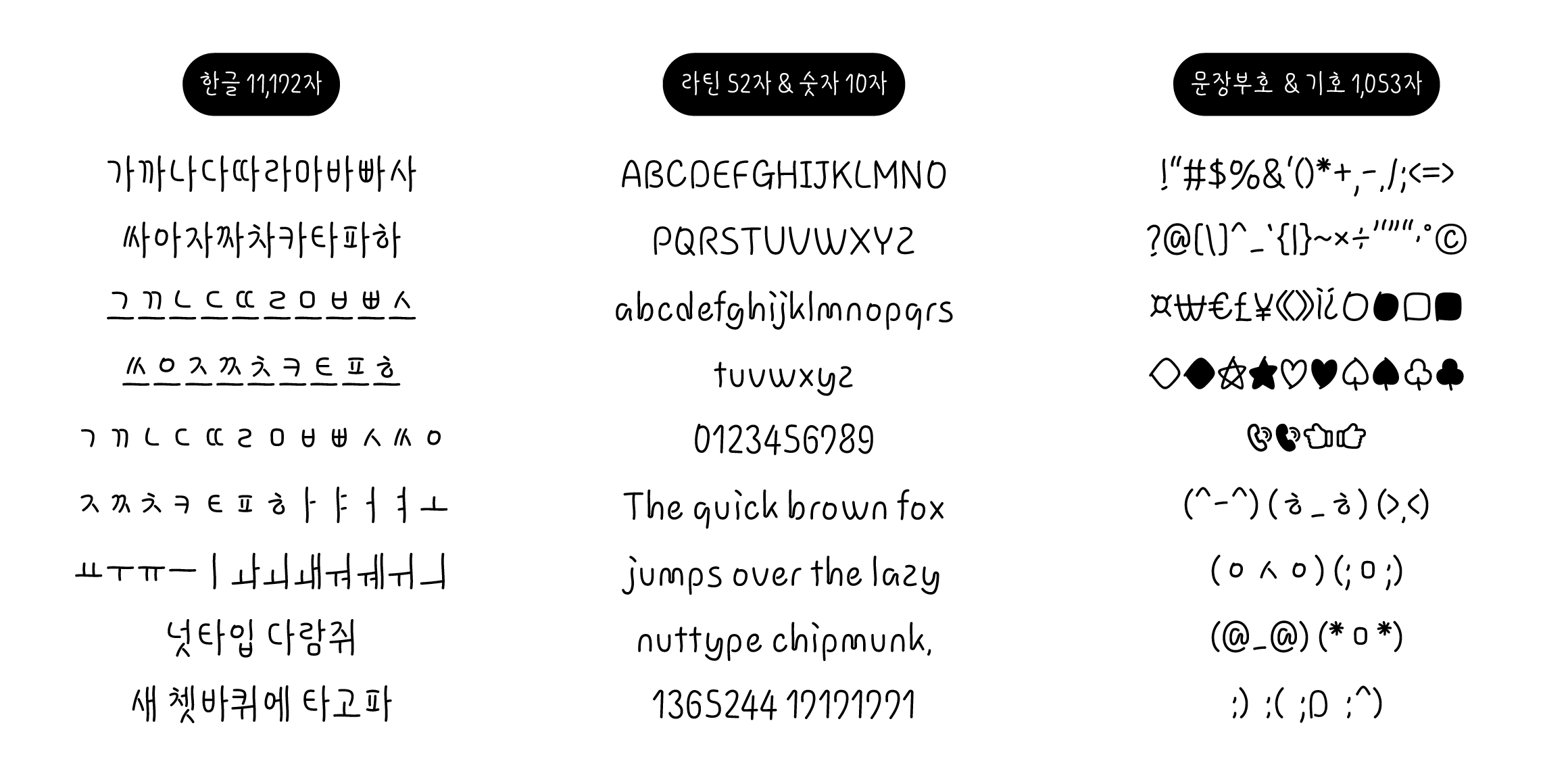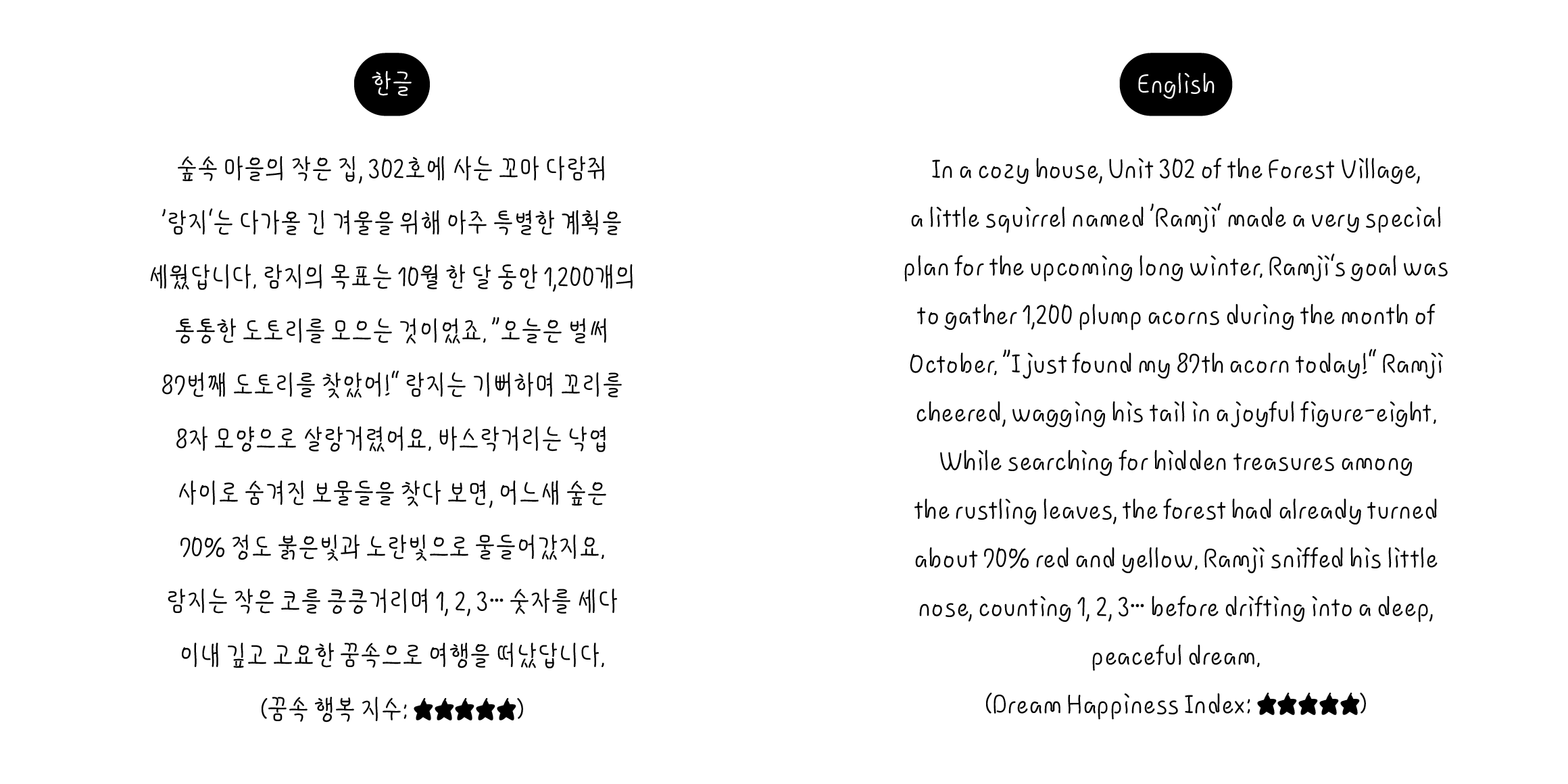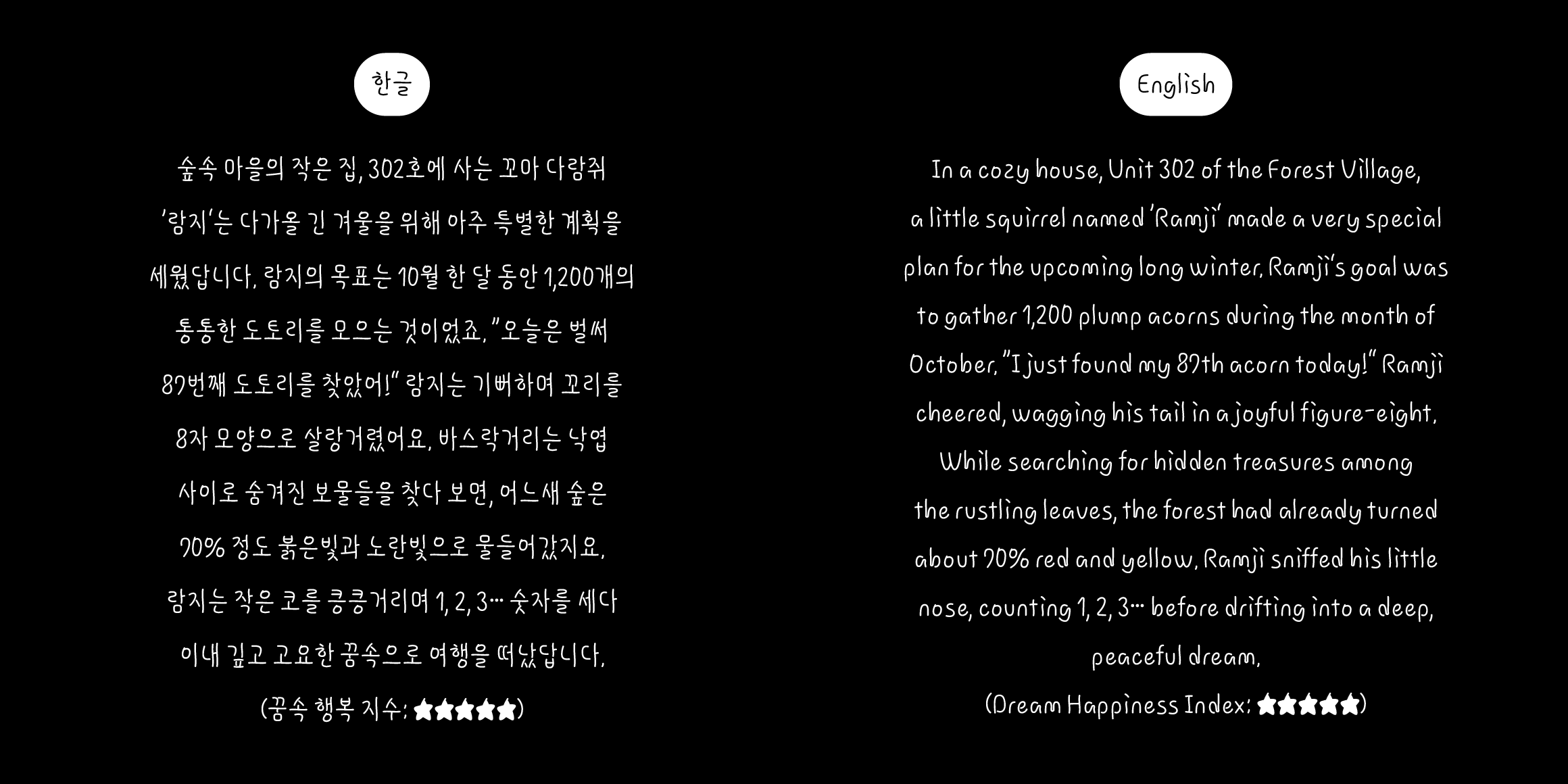
nut 병렬람지
Nuttype
분류 Script,손글씨
람지는 책을 한 권 끝까지 붙잡고 있지 않는다. 한쪽 손에는 철학, 다른 손에는 추리소설, 무릎 위에는 시집, 옆구리엔 만화책을 끼워 넣은 채 이리저리 들춰본다. 남들은 정신 산만하다 하지만, 람지에게는 이게 ‘균형 잡힌 독서 식단’이다.
• nut 병렬람지 / nut Parallel Ramji